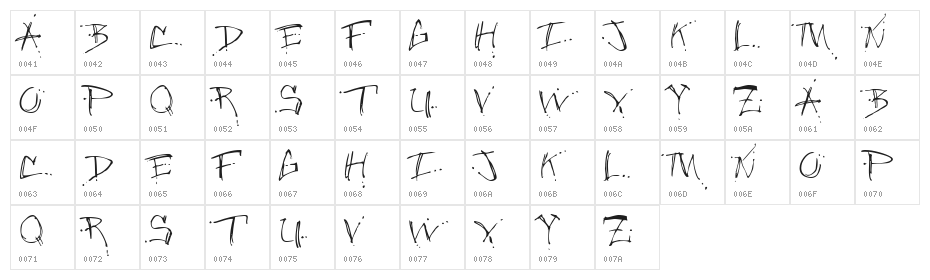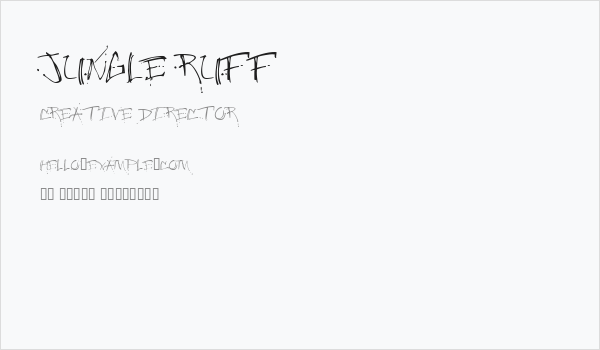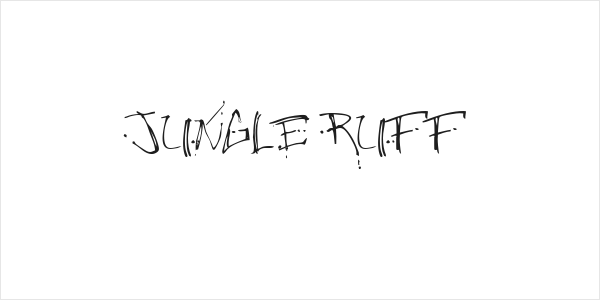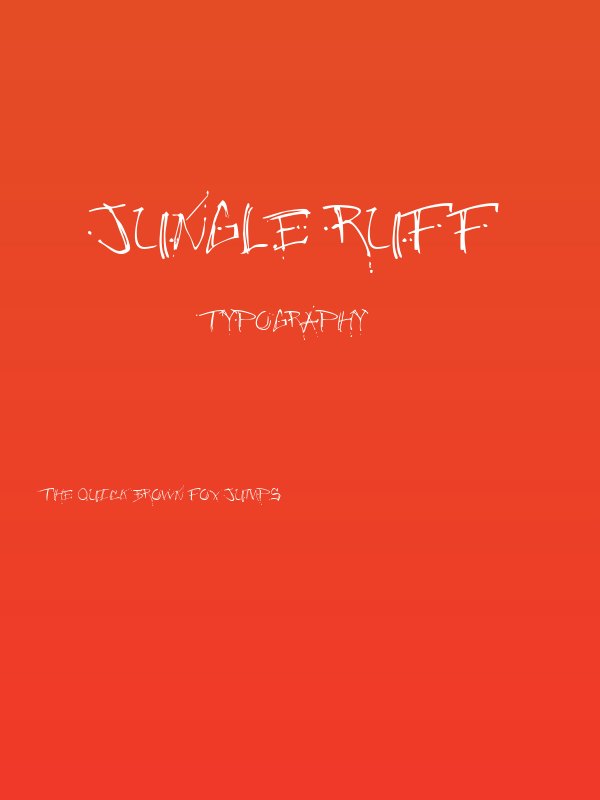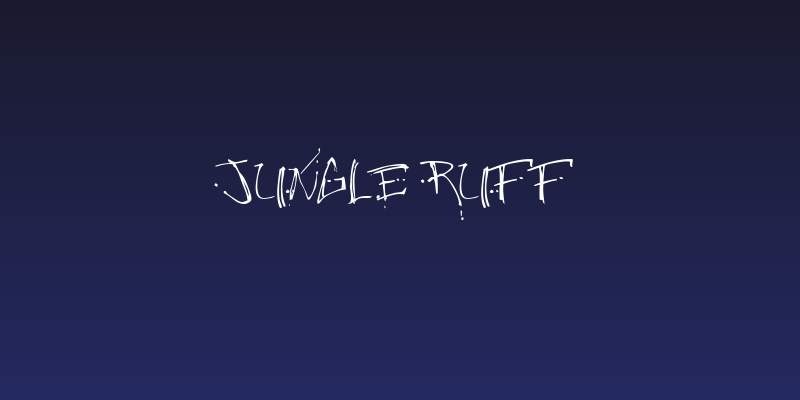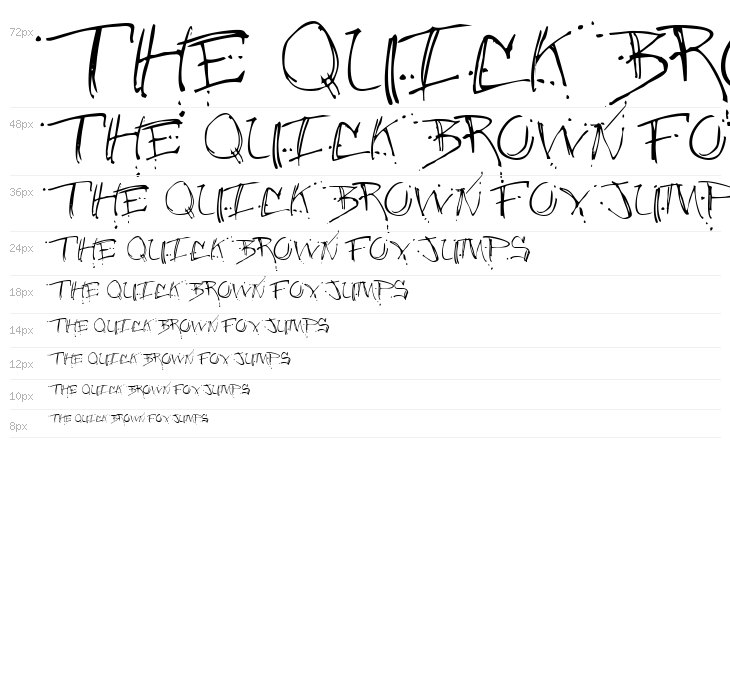
Jungle Ruff Font
✎ Script
| Gesamtstil | Modern, Artistic |
| Anwendungsfall | Logos, Headlines, Posters |
| Vorgeschlagene Projekte | Ideal for street art designs, music album covers, edgy branding, and creative posters. |